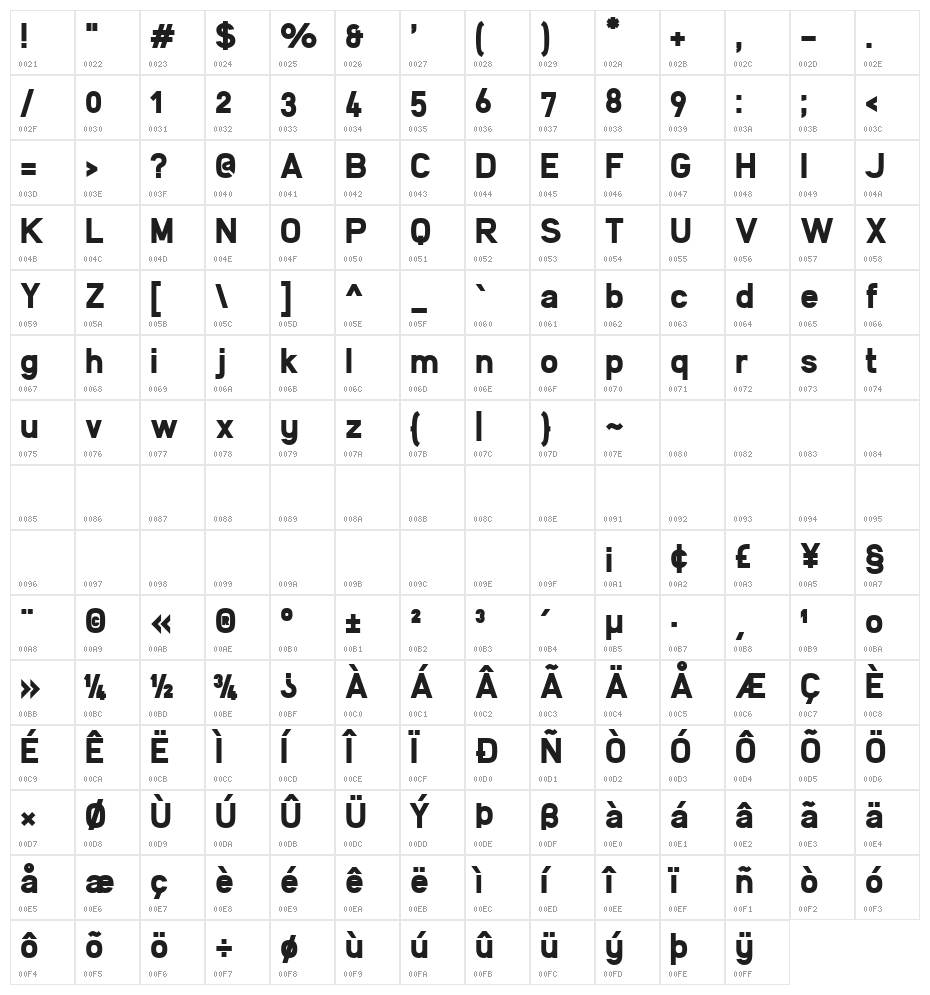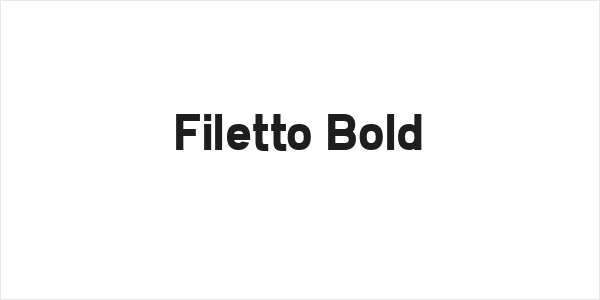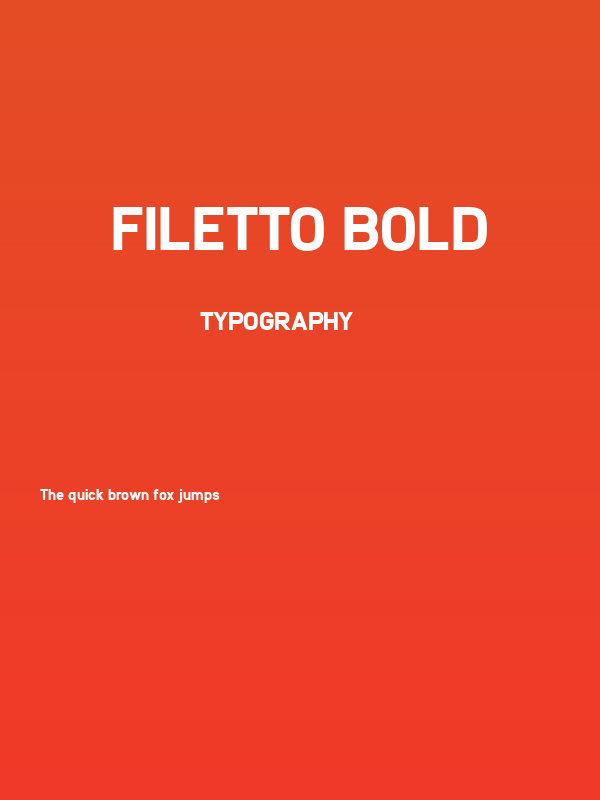
Filetto Bold Font
| Vorgeschlagene Projekte | Ideal for branding projects, headlines, posters, and digital media where a strong, impactful presence is needed. |